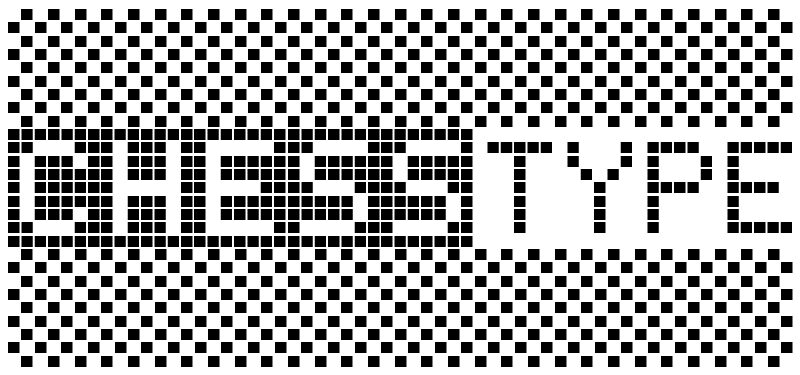
ChessType von Carl Krull ist eine kostenlose Pixel-Display-Schrift, die aus gleich großen quadratischen Kacheln aufgebaut ist. Ihre blockhaften Buchstaben ähneln Mustern auf einem Schachbrett, mit starren rechten Winkeln, offenen Zwischenräumen und einer ausgeprägt digitalen Silhouette.
Designer, die an Retrogames und technikbezogenen Veranstaltungen arbeiten, können sie für Titelbildschirme, Plakate und Merchandising einsetzen, da sich die kachelartige Konstruktion mühelos mit Rastern, Spielbrettern und Low-Resolution-Grafiken verbindet. Im Verlagswesen eignet sie sich für Rätselbücher oder Gaming-Magazine, wobei sie Titelzeilen eher zu einem Teil der brettartigen Grafik als zu gewöhnlicher Typografie macht.
ChessType is a black & white squared LCD pixel font. ChessType is created by Carl Krull. www.carlkrull.com - note: § + $ have been replaced with a filled and unfilled vertical pixelated line of space. ` + ± have been replaced with dotted vertical lines in opposition to one another. The $,§,± and ` still exist in the font-file, but in strange locations!